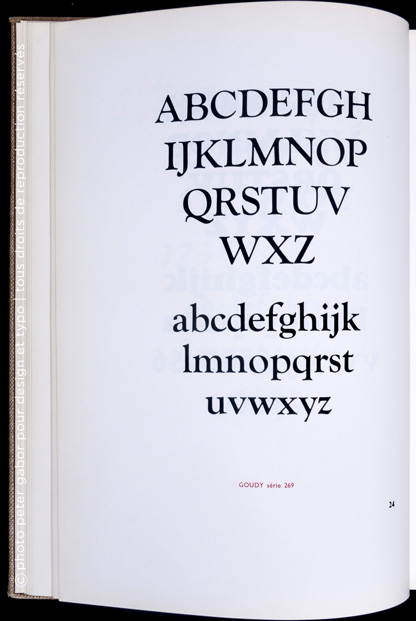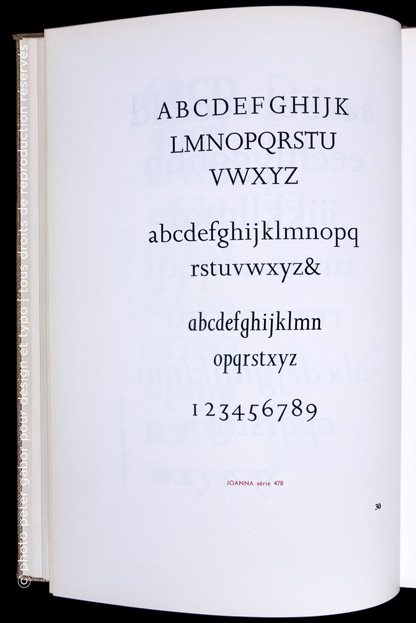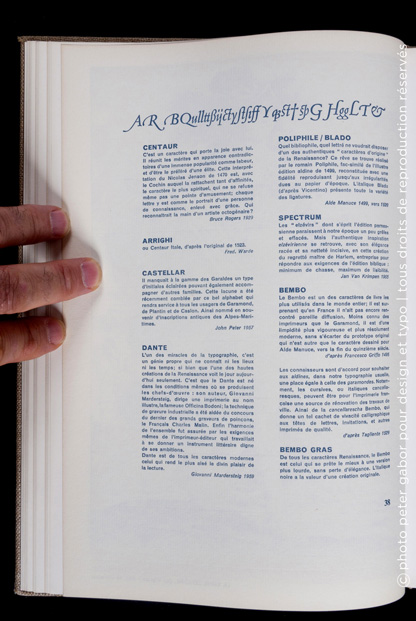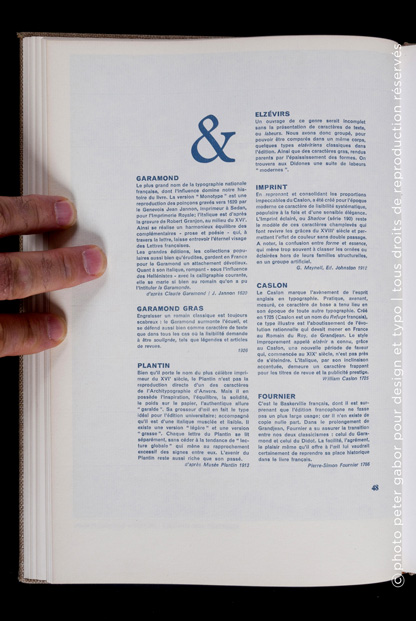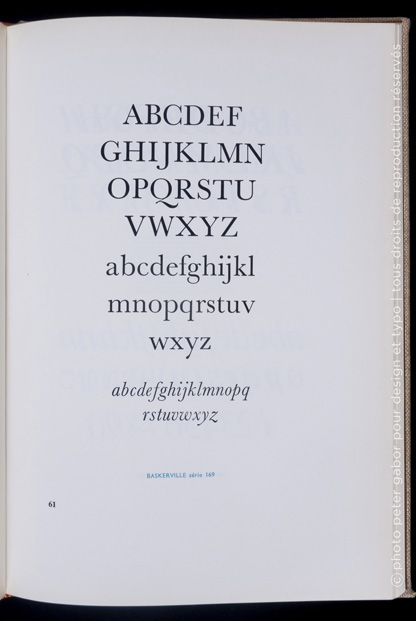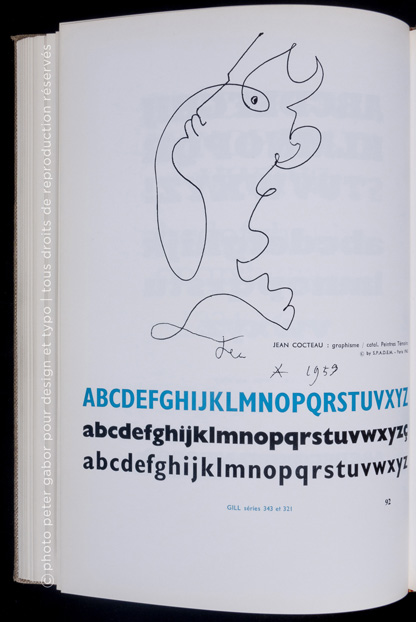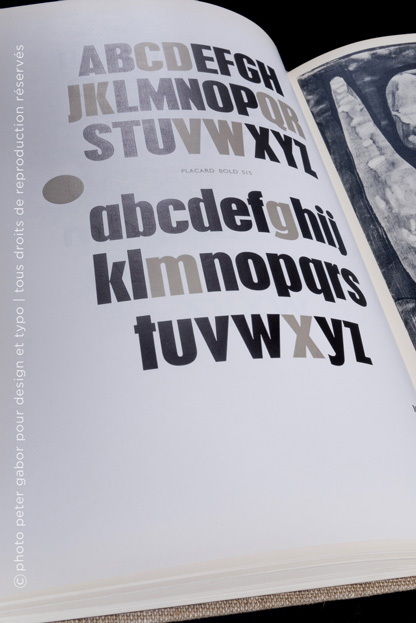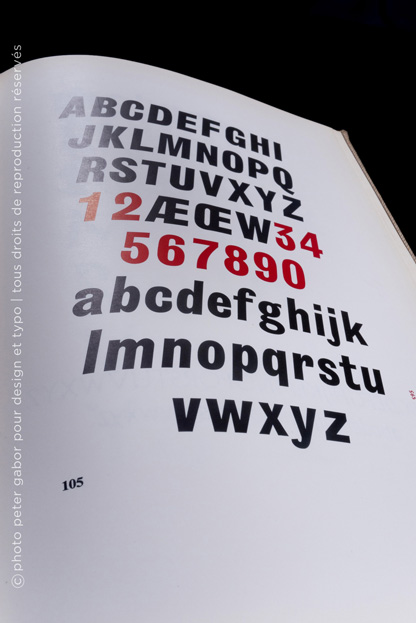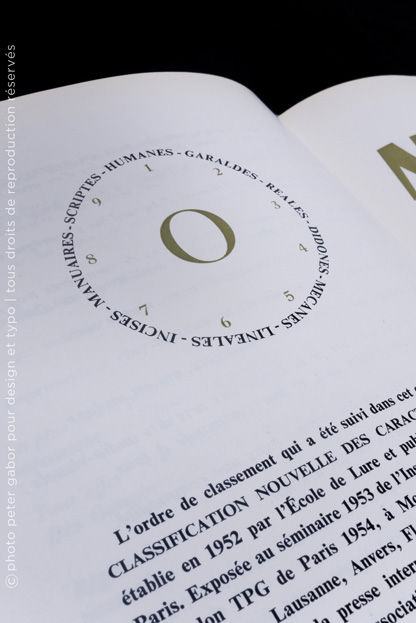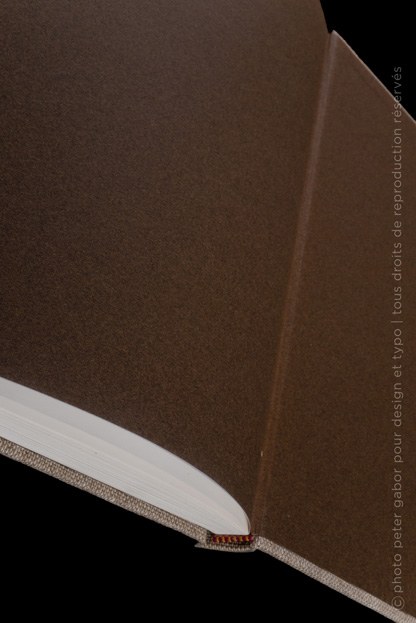
Maximilien Vox fait le point sur les 100 plus belles typos de la Monotype
C’est très exactement en 1961 que j’ai accompagné pour la première fois Paul Gabor aux Rencontres de Lure . Il venait de rejoindre les Compagnons en y faisant une conférence en hommage à la famille Knerr, imprimeurs hongrois plus que réputés. C’est à partir de cette date que j’ai fait mes classes auprès des plus grands typographes, puisque j’y ai rencontré Maximilien Vox, John Dreyfus, Jan Tschichold, Hermann Zapf, Albert Hollenstein et j’en passe et DES MEILLEURS. Et c’est précisément Albert Hollenstein qui allait présenter la nouvelle classification de Maximilien Vox, que nous utilisons encore nombre de fois. Non que ce soit la meilleure mais elle a un goût sûr pour faire la synthèse entre les formes typographiques et la chronologie de ces formes.
L’ouvrage ci-dessous, que vous pouvez consultez en détail en cliquant sur chacune des photographies, est une sorte de réponse de Vox à Zapf qui pouvait s’enorgueillir d’avoir fait un des plus beaux Manuale Typographicum en… 1957. Mais nous ne sommes pas là pour compter les points, plutôt à les aditionner. Les 100 alphabets présentés dans ce Manuel, représentent toute l’histoire et la philosophie de la firme Anglaise. Qualité, tradition et pas (trop) de compromis. Mais nous y reviendrons lors de la fin de ma publication des pages de Stanley Morison.
Appréciez la richesse et la versalité des formes alphabétiques, ainsi que la classe d’une présentation très traditionnelle. Et de regarder plus particulièrement les blancs tournants sur chaque page pour en mesurer les codes d’élégances. Enjoy your visit sur Design et Typo.